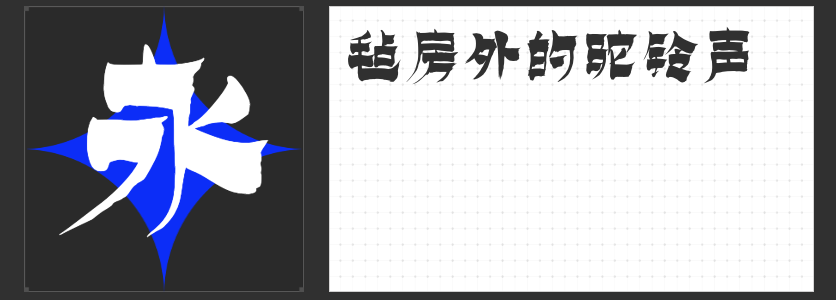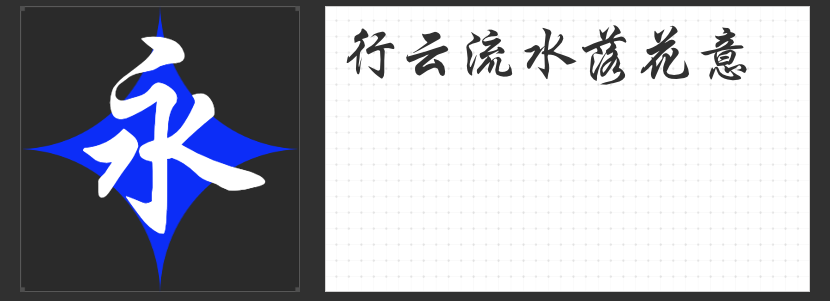
渲染新中式气氛!四款大人气字体推荐
在设计中,字体的选择往往决定了作品的整体风格和氛围。近年来,“新中式”风格在设计界悄然兴起,它将传统元素与现代审美相结合,打造出独具韵味的作品。今天,为大家推荐四款适用于设计中的“新中式”字体。
这款字体以其独特的毛笔手书风格吸引了众多设计师的目光。字体的笔画厚重,撇字清晰从容,展现出一种灵性的美感。框架醒目,字型端庄,使得整个字体风格统一而和谐。无论是包装印刷还是广告设计,造字侠永刚漆书简繁都能为作品增添一份浓郁的文化气息。
2.造字侠磅礴简繁
这款字体中正感官丰富,运笔富有节奏感。笔画粗细变化明显,略带飞白效果,转折处方圆相结合,展现出一种磅礴大气的美感。它适用于各种需要展现力量感和层次感的设计作品。
则是一款充满古风韵味的硬笔手写字。它的名字来源于《西游记》中玉皇大帝的居所灵霄宝殿,字体笔画硬挺利落,字形古风劲萧,饱满均匀。结构布局沉稳,笔力劲健,使得这款字体非常适合用于仙侠、网游等海报标题用字,能够瞬间抓住观众的眼球。
4.励字行楷简繁
则介于行书的活泼与楷书的端正之间,展现出一种秀美适意的风格。笔画流畅,点画呼应,舒缓自如,读来如行云流水,一气呵成。这款字体具有较强的动势美感,适用于各种需要展现灵动感和流畅感的设计作品。
总的来说,这四款“新中式”字体各具特色,能够满足不同设计作品的需求。它们不仅传承了传统文化的精髓,还融入了现代审美的元素,使得设计作品更加具有文化韵味和时代感。希望这些推荐能够帮助大家在设计中更好地选择字体,打造出更加出色的作品。